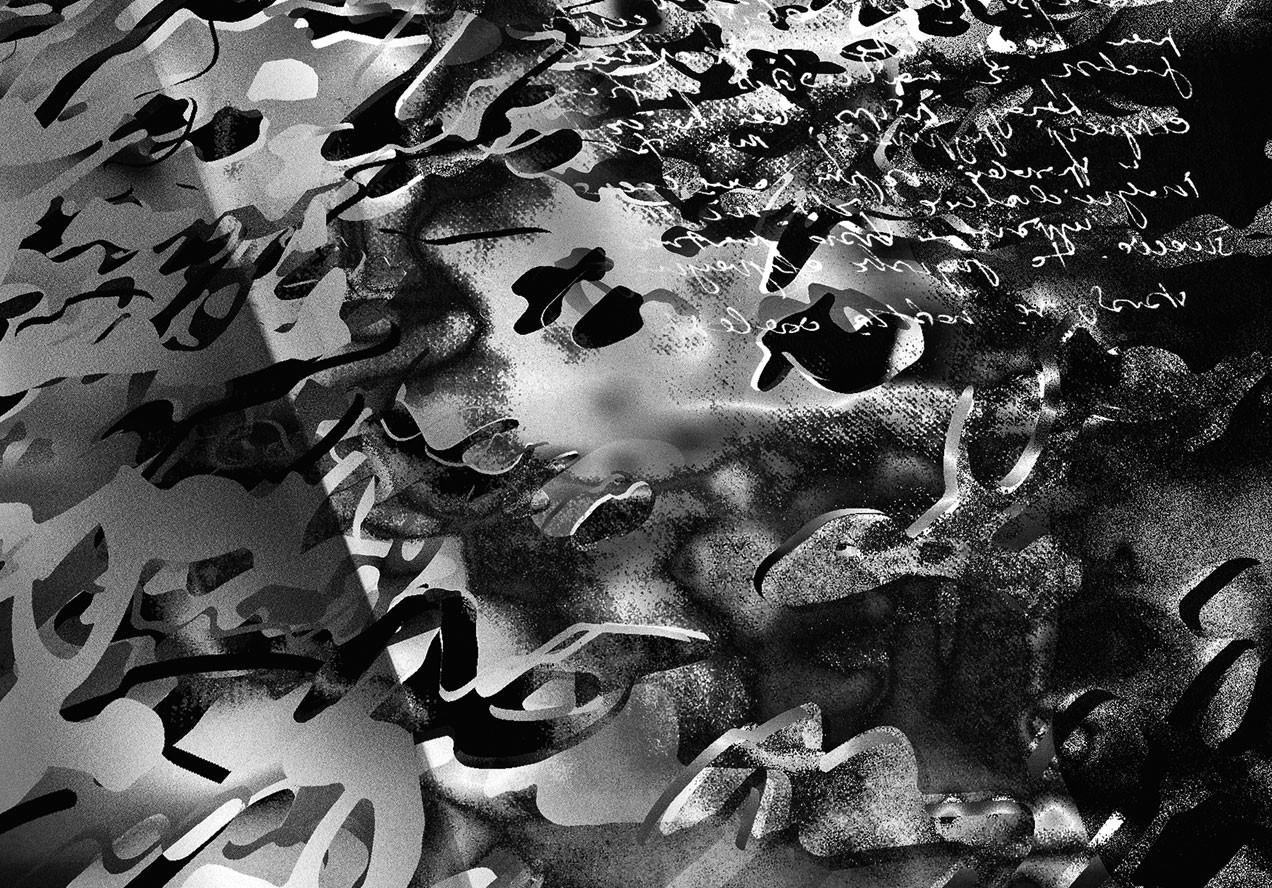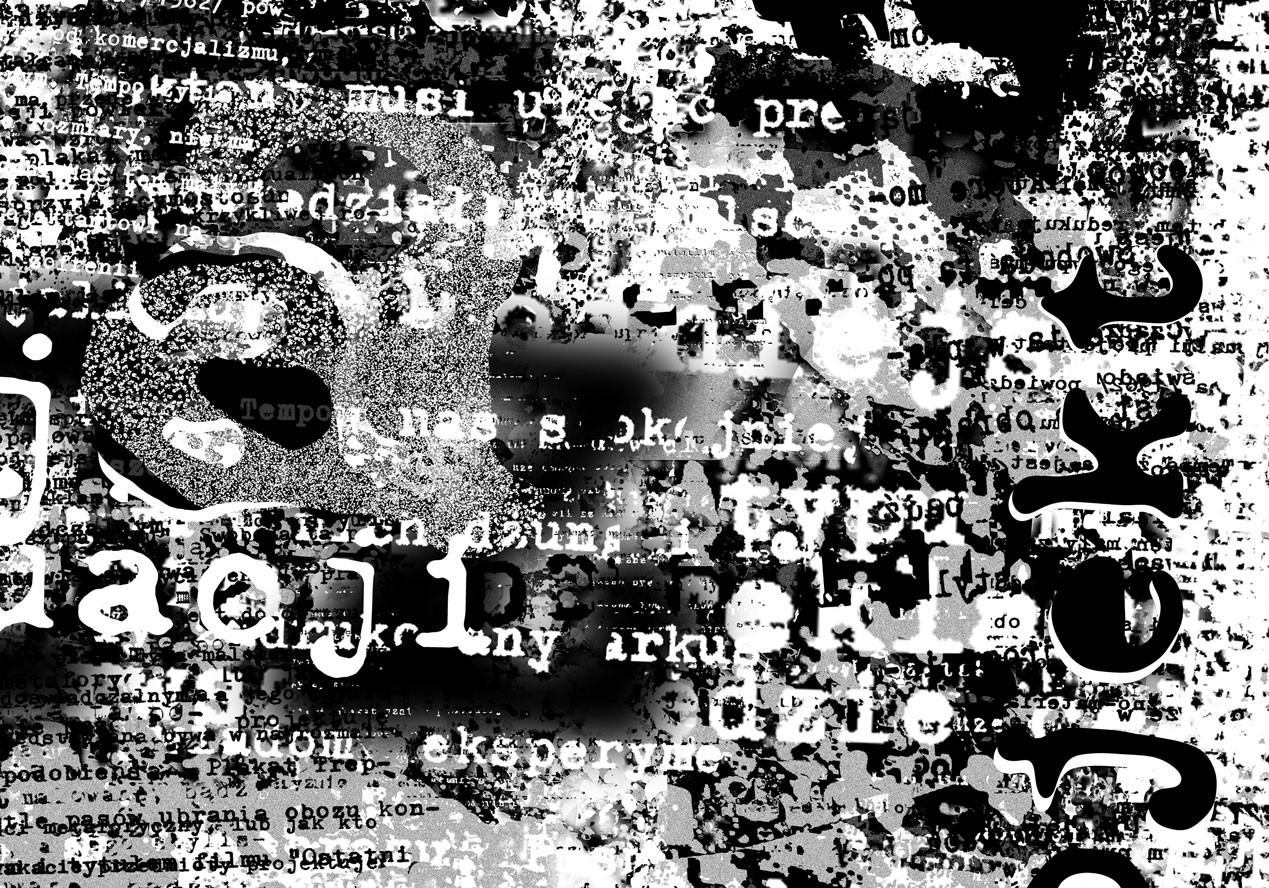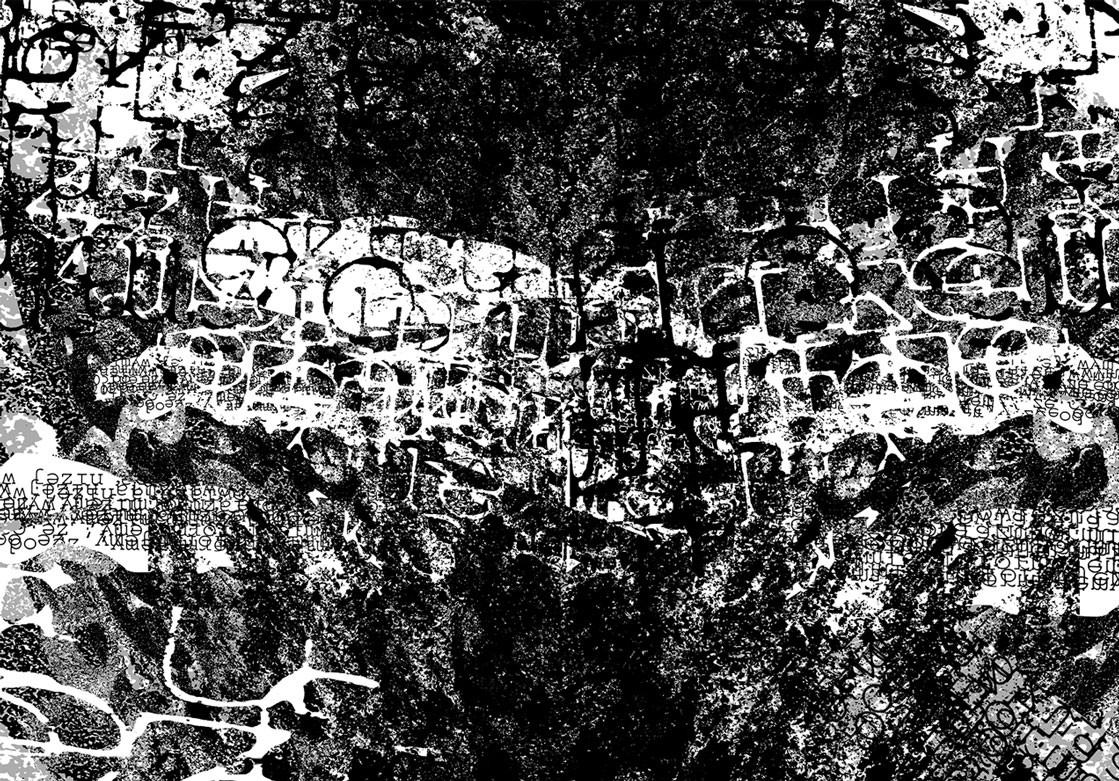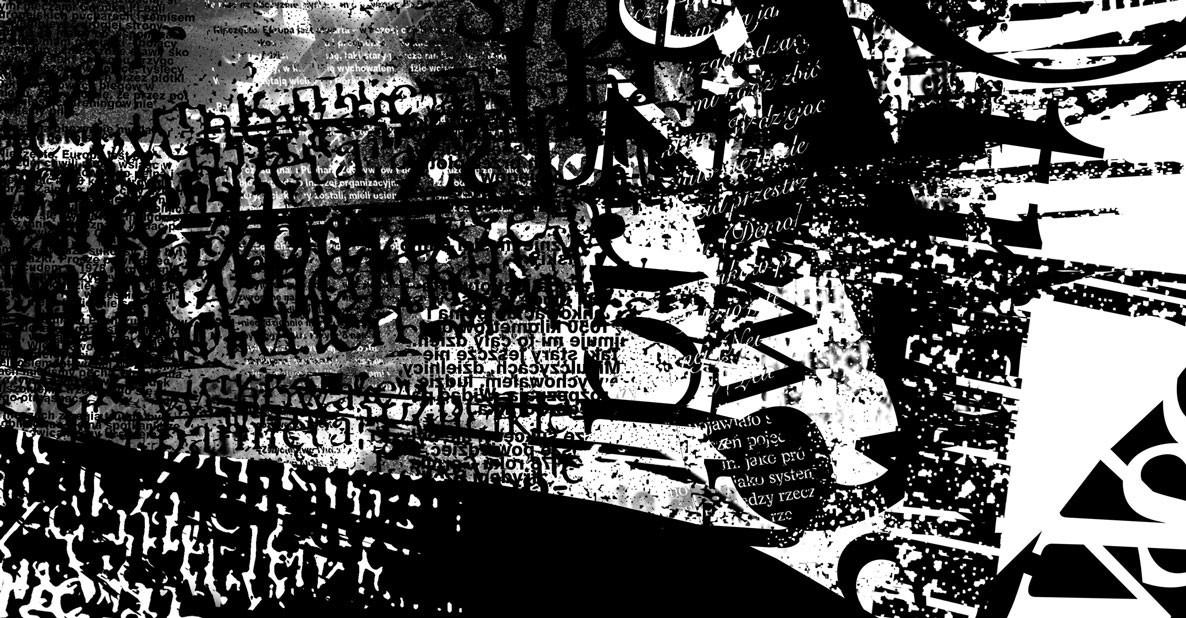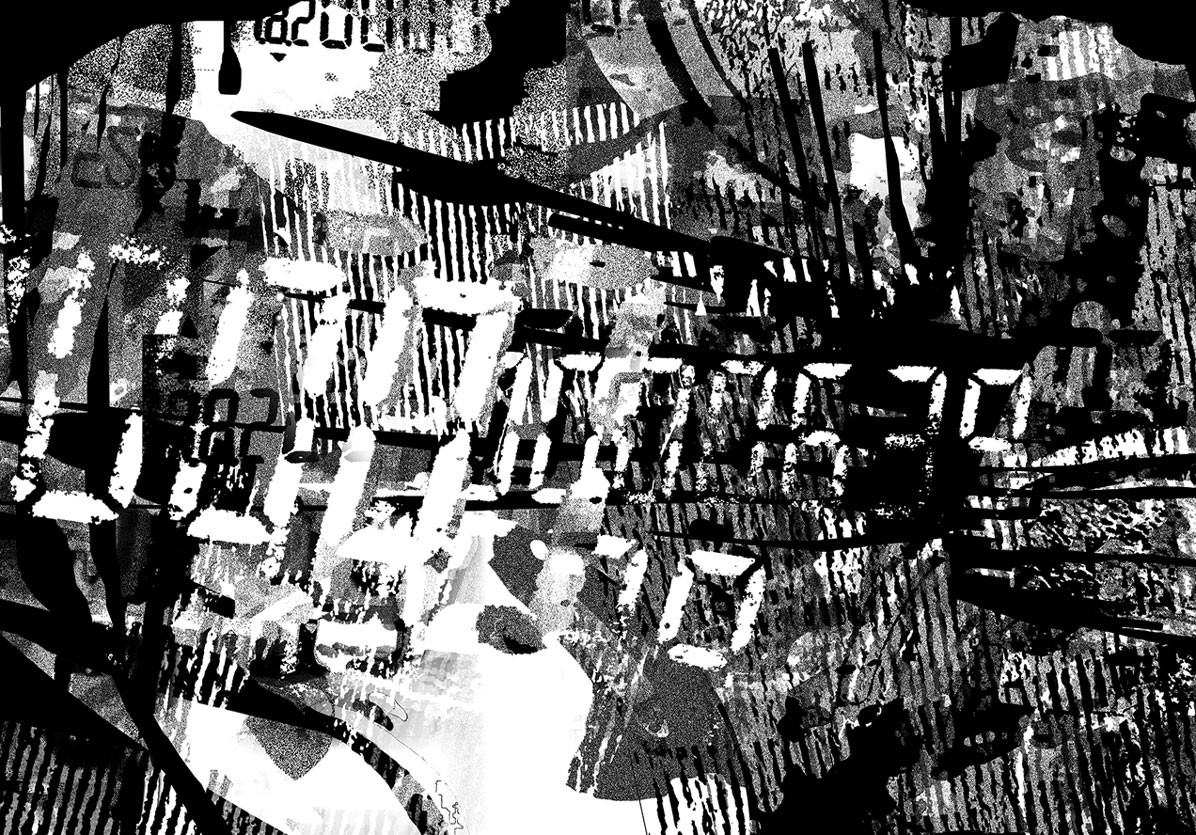
Zapraszam na wystawę cyfrowych obrazów inspirowanych literą, słowem, materią i strukturą tekstów.
Prace są kilkuletnim graficznym dialogiem, weryfikacją i eksperymentem inspirowanym praktyką projektową i dydaktyczną związaną z typografią. Realizacje z zakresu grafiki projektowej stanowią jak gdyby przedpola analiz i kreacji autonomicznych obrazów cyfrowych łączących aspekty wizualne z różnorodnością zapisów tekstowych.
Cykl jest przestrzenią twórczych rozwiązań łączących warsztat klasyczny z cyfrowym. Następuje tu wielokrotna „fuzja" materii i procesów graficznych (zapisy odręczne, druki, litery i fragmenty fotografii) stwarzających wspólnie nowe, wyrazowe jakości kreowanych prac. Najistotniejszym elementem i punktem odniesienia w TypoGrafiach jest litera i jej wielokrotność. Wyznacza ona początek i koniec cyfrowych poszukiwań i stanowi fundamenty obrazowo-typograficznych kontekstów.